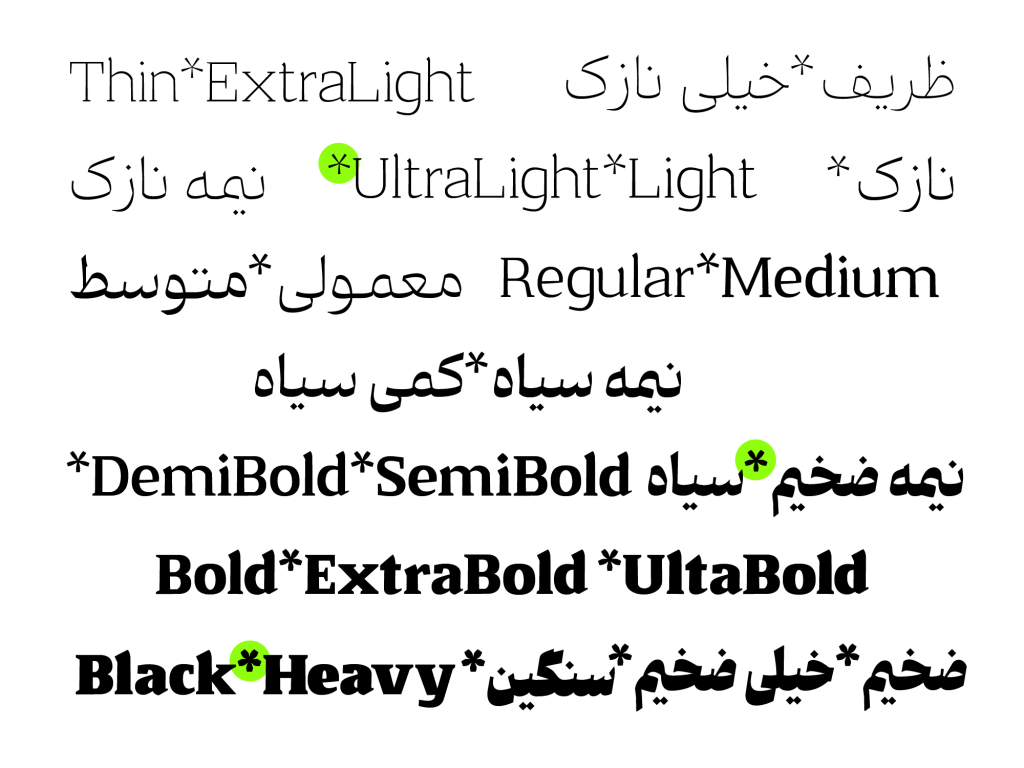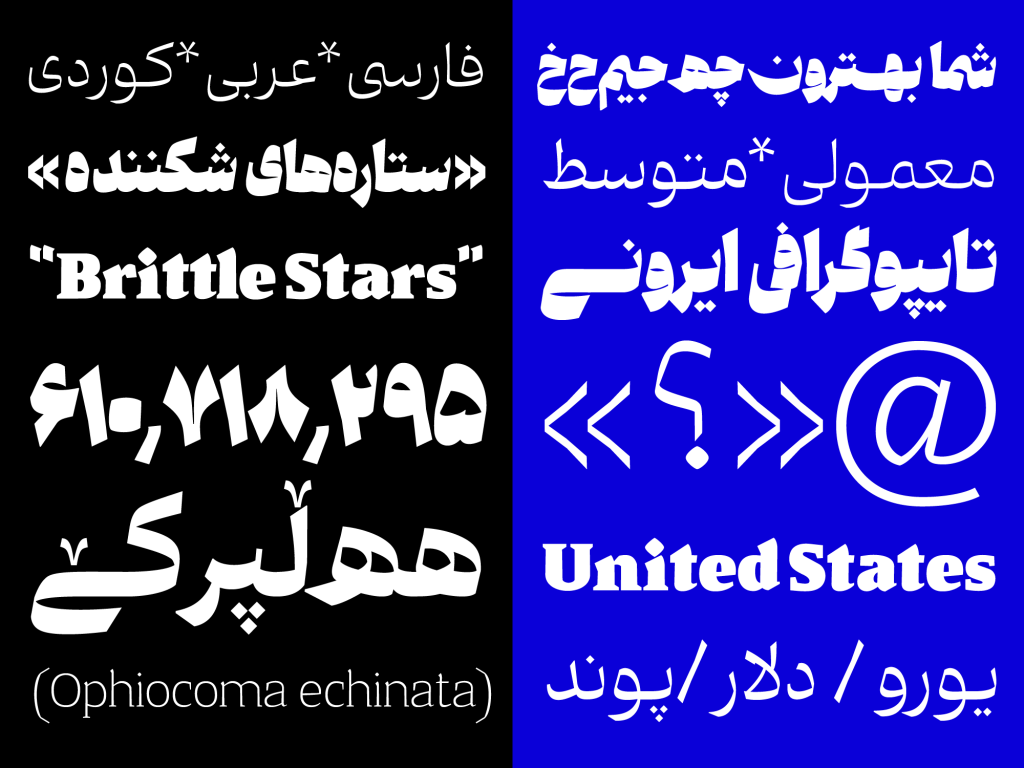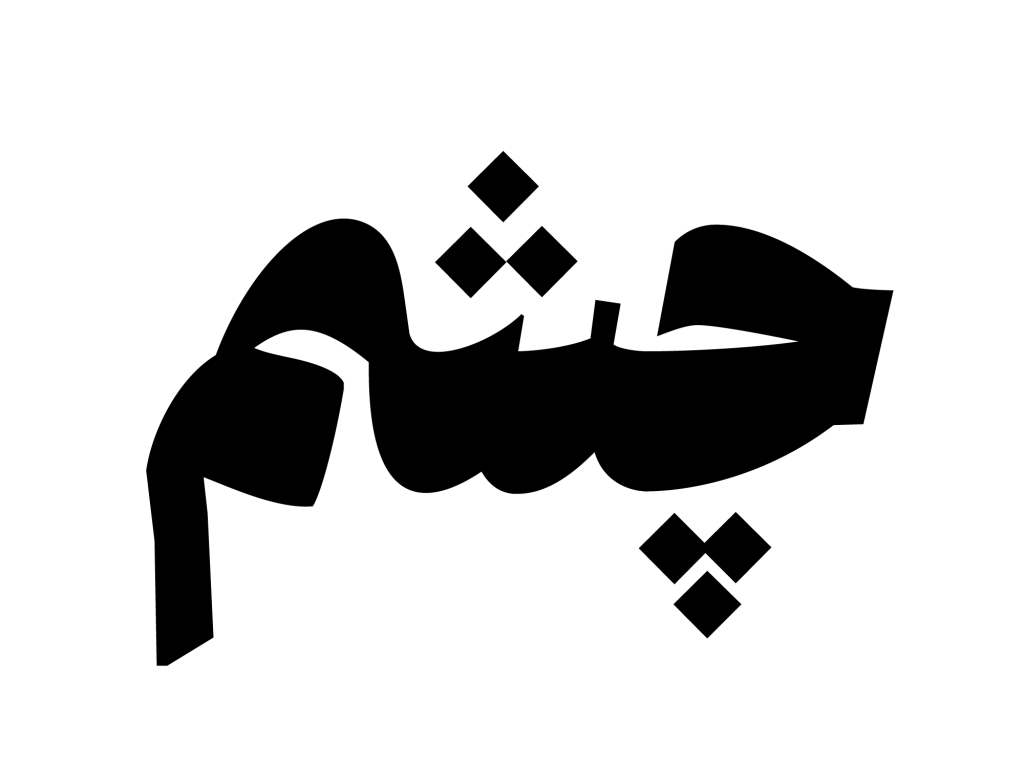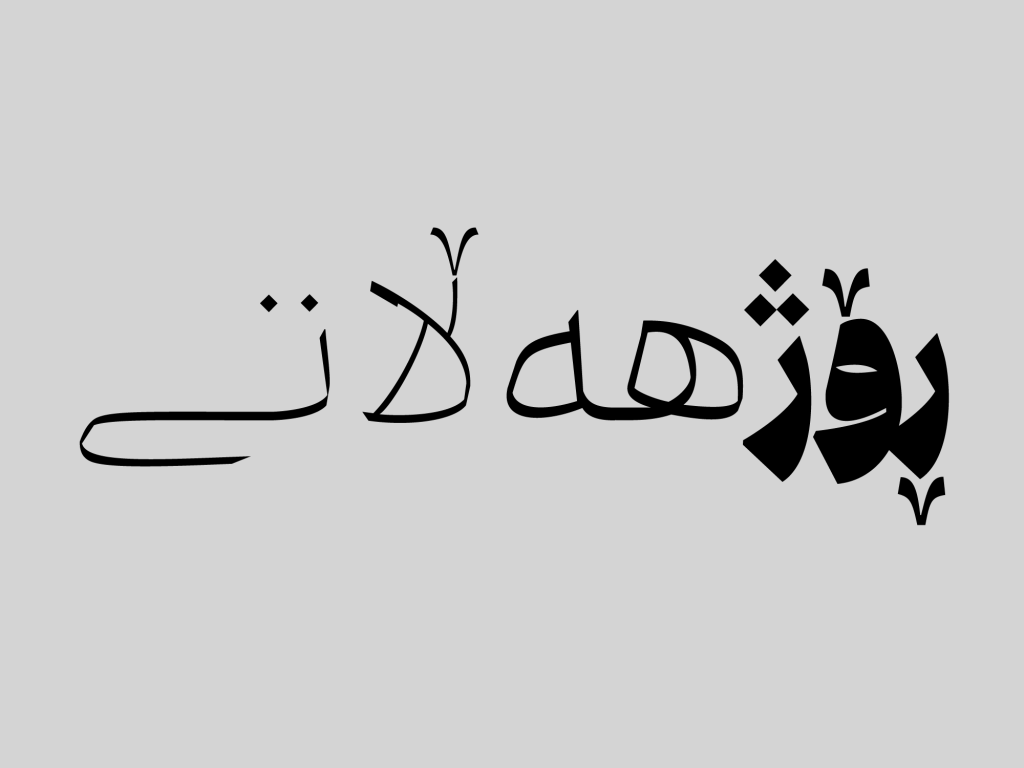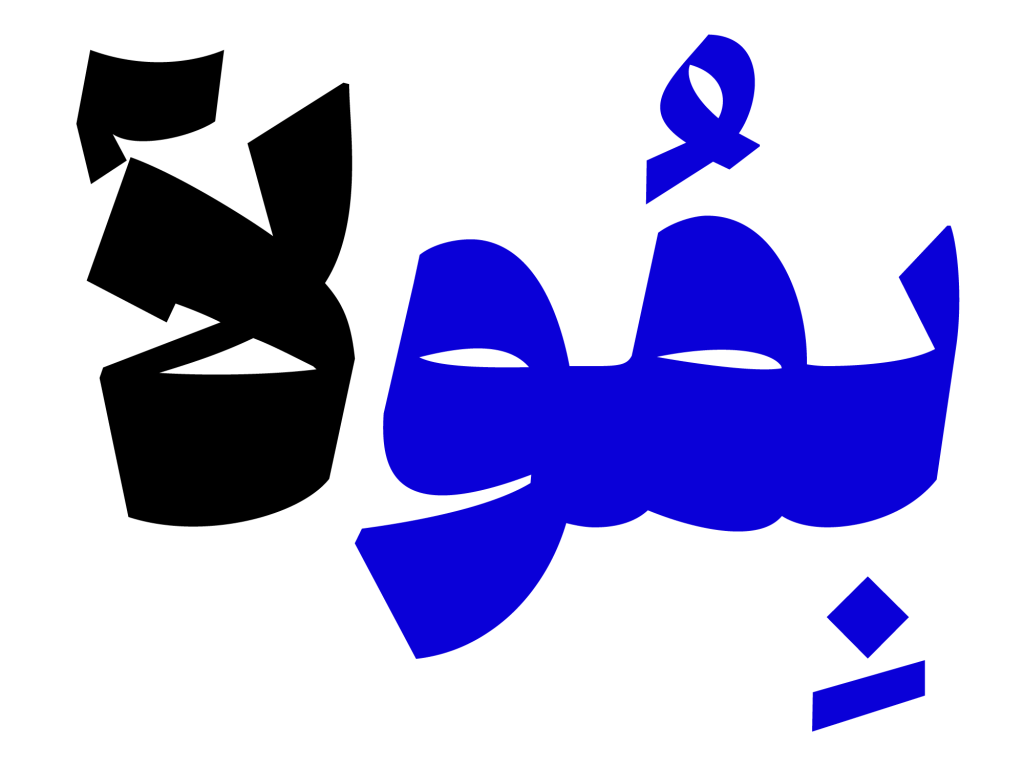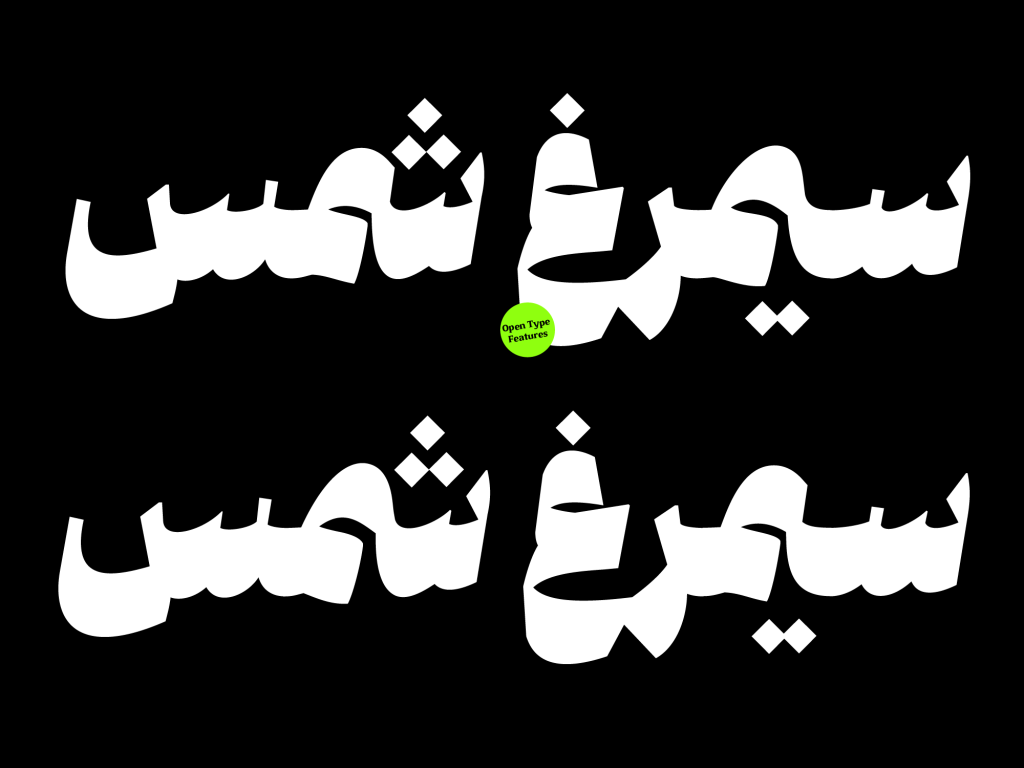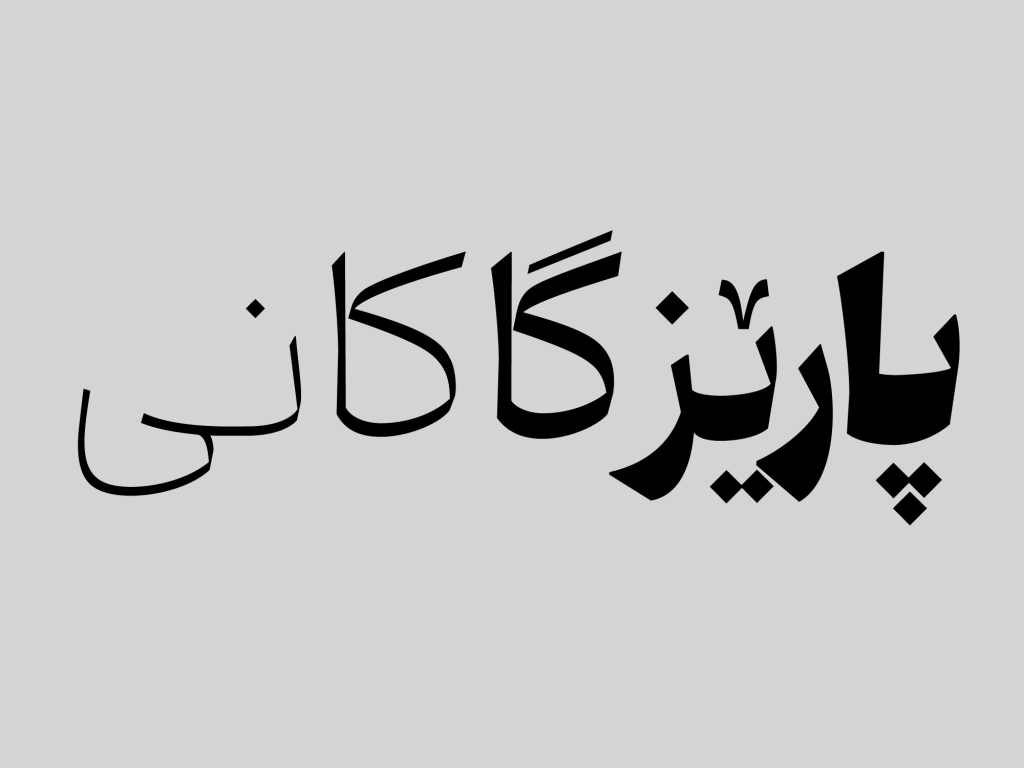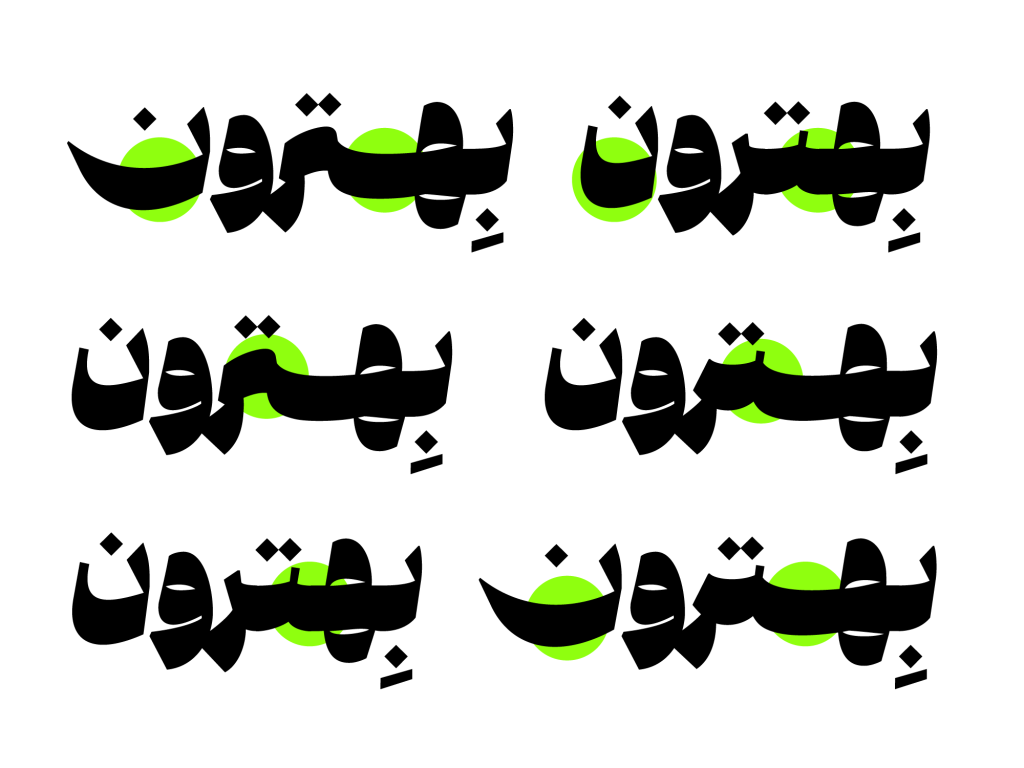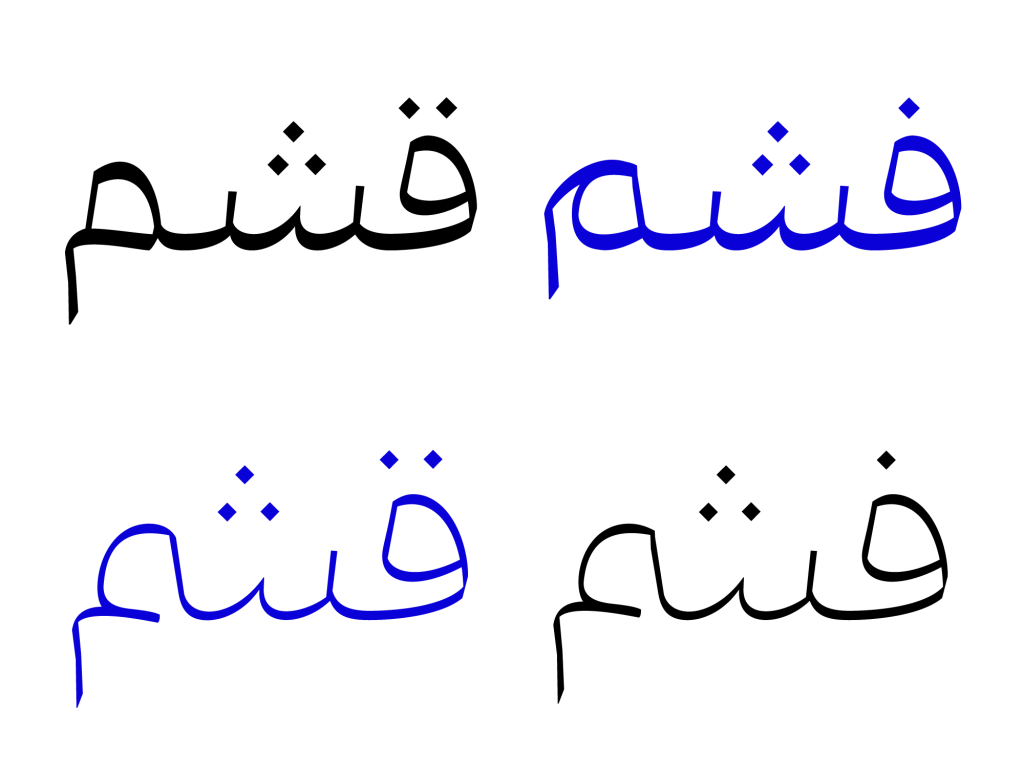
فونت وِنوو
فونت ونوو قلمی از خانواده خط اصیل نسخ است اما به گونه ای فرم های ساختاری حروف خود را طراحی نموده است که با فضا و اتمسفر نوشته های امروزی نه تنها بیگانه نیست بلکه مدرن و نو است. با نگاه اجمالی می توان دریافت که این تایپ فیس دارای کنتراست در ضخامت می باشد که هرچه اوزان قلم سنگین تر می شود کنتراست هم به تبع آن بیشتر می شود.
هدف اولیه از طراحی این قلم شکل بخشی و خلق ایده ای جدید برای تایپ فیس های حجیم و سنگین وزن بود اما در طول مسیر طراحی به یک خانواده مدرن گسترش یافت تا بتواند نیازهای مختلف را برآورده کند. همانگونه که در ابتدای این مقاله خدمت شما عزیزان گفته شد . قلم ونوو قابلیت ها متعدد و کاملی را برای طراحان ارائه می دهد.
تایپ فیس ونوو دارای خانواده کاملی از وزن های های مختلف است . ونوو با بهره بردن از 13 وزن مختلف از ظریف تا خیلی سنگین همه نیاز طراحان را برای خلق آثار با تنوع وزنی مختلف مهیا ساخته است. کمتر قلمی در تایپوگرافی فارسی را می توان یافت که این حجم از تنوع وزنی را دارا باشد.
یکی از ویژگیهای مهم این تایپ فیس ، تعامل بین ضخامت حروف است که به آن جذابیت و استحکامی مدرن میبخشد. این خصوصیت بین فرمهای سخت و نرم، ونوو را به یک تایپفیس منحصر بهفرد تبدیل کرده است. میتوانید در کاربردهایی مانند تیترهای مطبوعاتی، انواع بستهبندی، گرافیک محیطی، وب و محتواهای رسانههای اجتماعی از این قلم زیبا نهایت بهره مندی را برده و از تجربه کردن آن لذت ببرید.
حروف و ترکیبات جایگزین در فونت ونوو
از دیگر قابلیت های ونوو که سبب خلق تنوع و زیبایی و جذابیت دو چندان در طراحی می شود و روح و نشاط تازه ای به نوشتار می بخشد. پشتیبانی از حروف و ترکیبات جایگزین و متنوع است. می توانید بعد از دانلود در بسته راهنمای این محصول نحوه استفاده از این ترکیبات جایگزین را مشاهده کنید.
در این تایپ فیس حروف و گلیف های مربوط به سایر زبان ها در آن طراحی شده است بنابراین این قلم قابلیت پشتیبانی از زبان های انگلیسی , عربی , کوردی را علاوه بر فارسی دارد. شما می توانید ونوو را با 5 درصد تخفیف از سایت مرجع آن دانلود و خرید کنید . کافی است پس از کلیک بر روی لینک زیر کد fontziba را مطابق تصویر زیر در قسمت تخفیف های سایت مرجع فروش آن وارد کنید.
ونوو دارای شخصیتی جدی شجاع است و به دنبال جذب نگاه مخاطبان و بینندگان به خود می باشد. این قلم مناسب متون کوتاه و عناوین می باشد . در زیر تصاویری نمونه از این تایپ فیس برای شما عزیزان ارائه گردیده است.